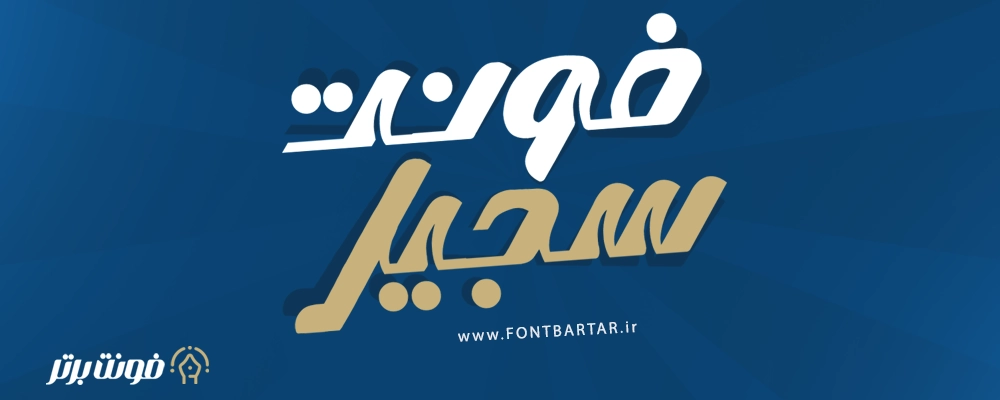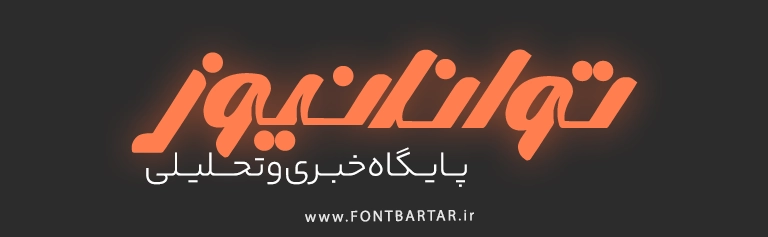
فونت سجیل
فونت فارسی سجیل
Sejil Font
دانلود فونت فارسی سجیل – فونت بولد و خلاقانه برای طراحی تبلیغاتی
اگر به دنبال یک فونت فارسی خاص، قدرتمند و تاثیرگذار هستید که به پروژه‌های گرافیکی شما جلوه‌ای حرفه‌ای ببخشد، فونت سجیل گزینه‌ای ایده‌آل برای شماست. این فونت با استایل خاص، ضخامت مناسب و طراحی منحصربه‌فرد خود، انتخابی بی‌نظیر برای طراحی لوگو، پوستر، جلد کتاب، تیزرهای تبلیغاتی و حتی کاور شبکه‌های اجتماعی است.
یک فونت فارسی و گرافیکی جدید به نام سجیل معرفی می شود که در 5 فرمت متفاوت منتشر شده است ، فونت فارسی سجیل باحالت های گرافیکی فوق العاده حرفه ای این امکان را برایتان فراهم میکند تا به زیبایی حروف را کنار هم قرار دهید و در طراحی های خود از جمله لوگوتایپ فارسی و یا تایپوگرافی استفاده کنید.
ویژگی‌های فونت سجیل
• طراحی جسورانه با خطوط منحنی و زاویه‌دار
• وزن بولد و مناسب برای عنوان‌ها
• نمایش زیبا در فرمت‌های بزرگ چاپی و دیجیتال